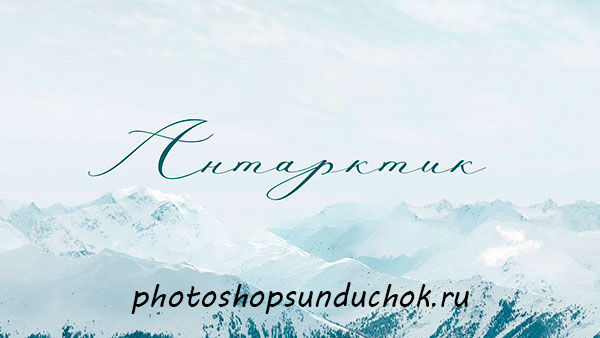
Элегантный шрифт Antarctic
Элегантный шрифт
Antarctic
Antarctic – каллиграфический элегантный шрифт.
Шрифт идеально подходит для свадебных событий, свадебного приглашения, свадебного журнала, плакатов, анонсов и многих других проектов.
Отличные переходы между буквами.
Шрифт имеет верхний и нижний регистр.
Шрифт поддерживает латиницу и кириллицу.
Элегантный шрифт Antarctic